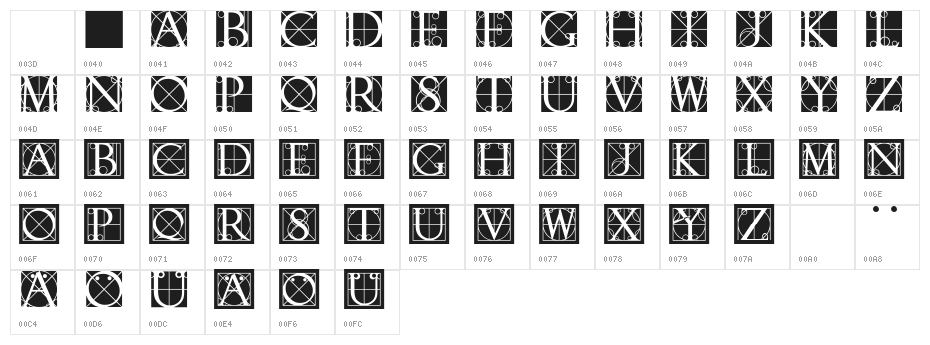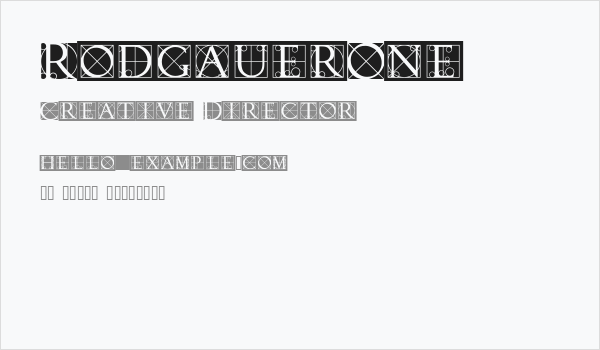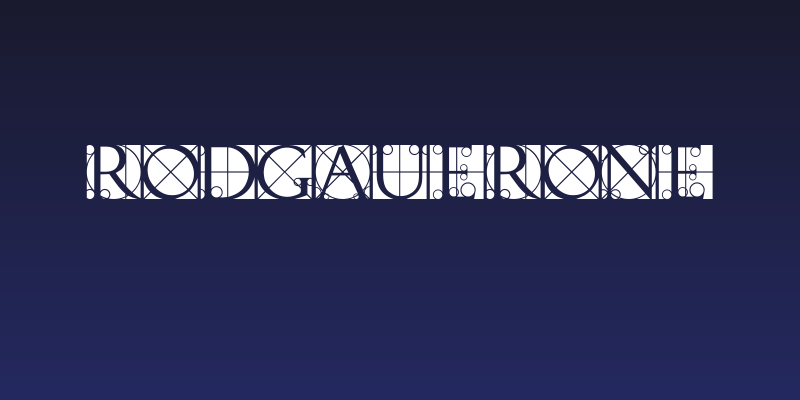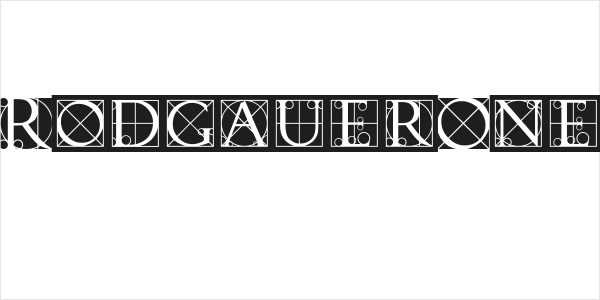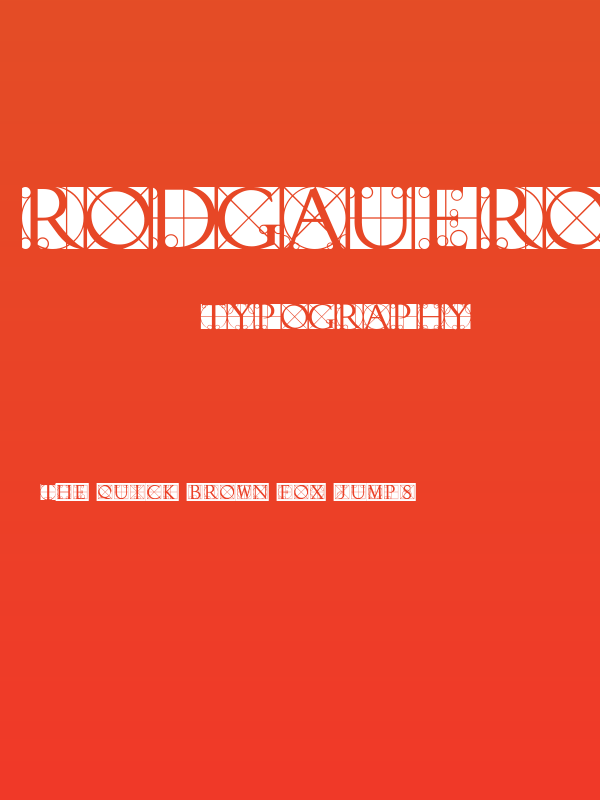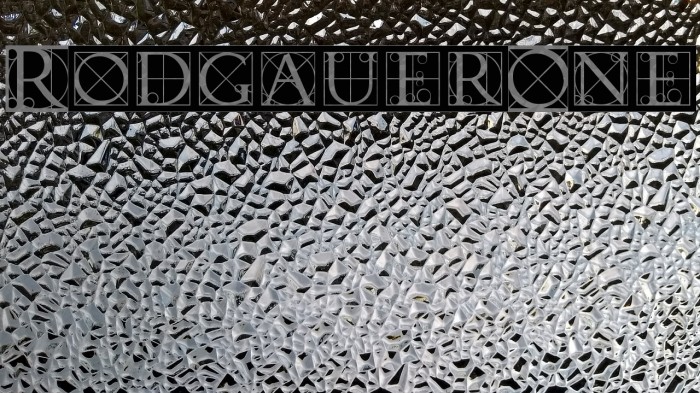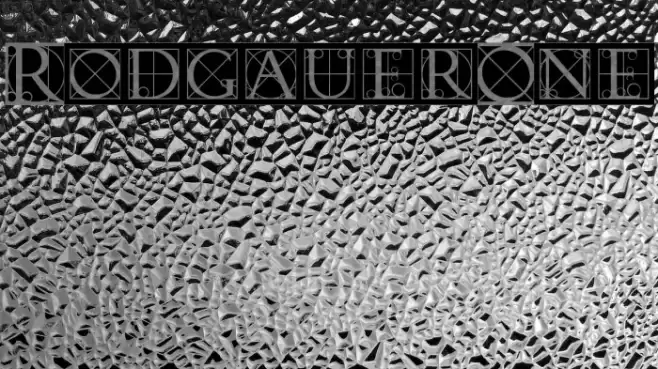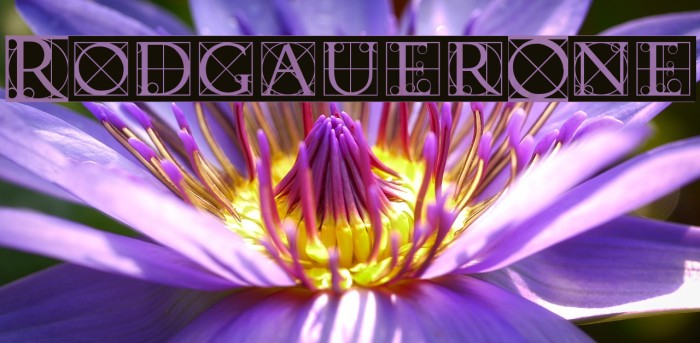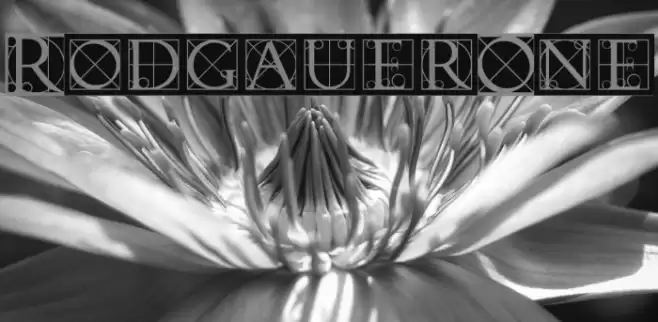
RodgauerOne Font
Fonts by Manfred Klein - manfred-klein.ina-mar.com
| Категория | Crazy |
| Общий стиль | Vintage, Decorative |
| Область применения | Logos, Headlines, Decorative text |
| Рекомендуемые проекты | Ideal for use in luxury branding, wedding invitations, high-end product packaging, and decorative posters. |